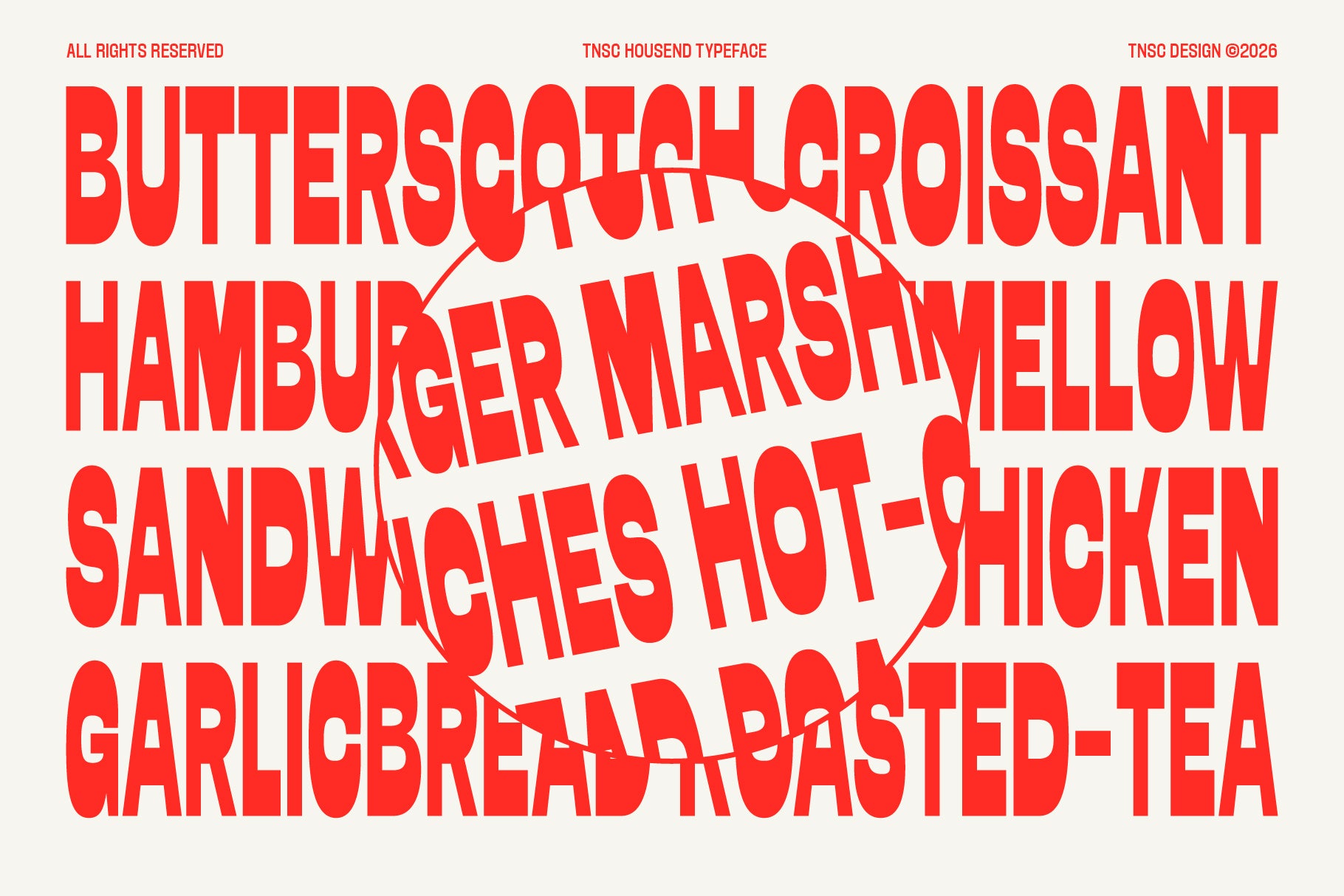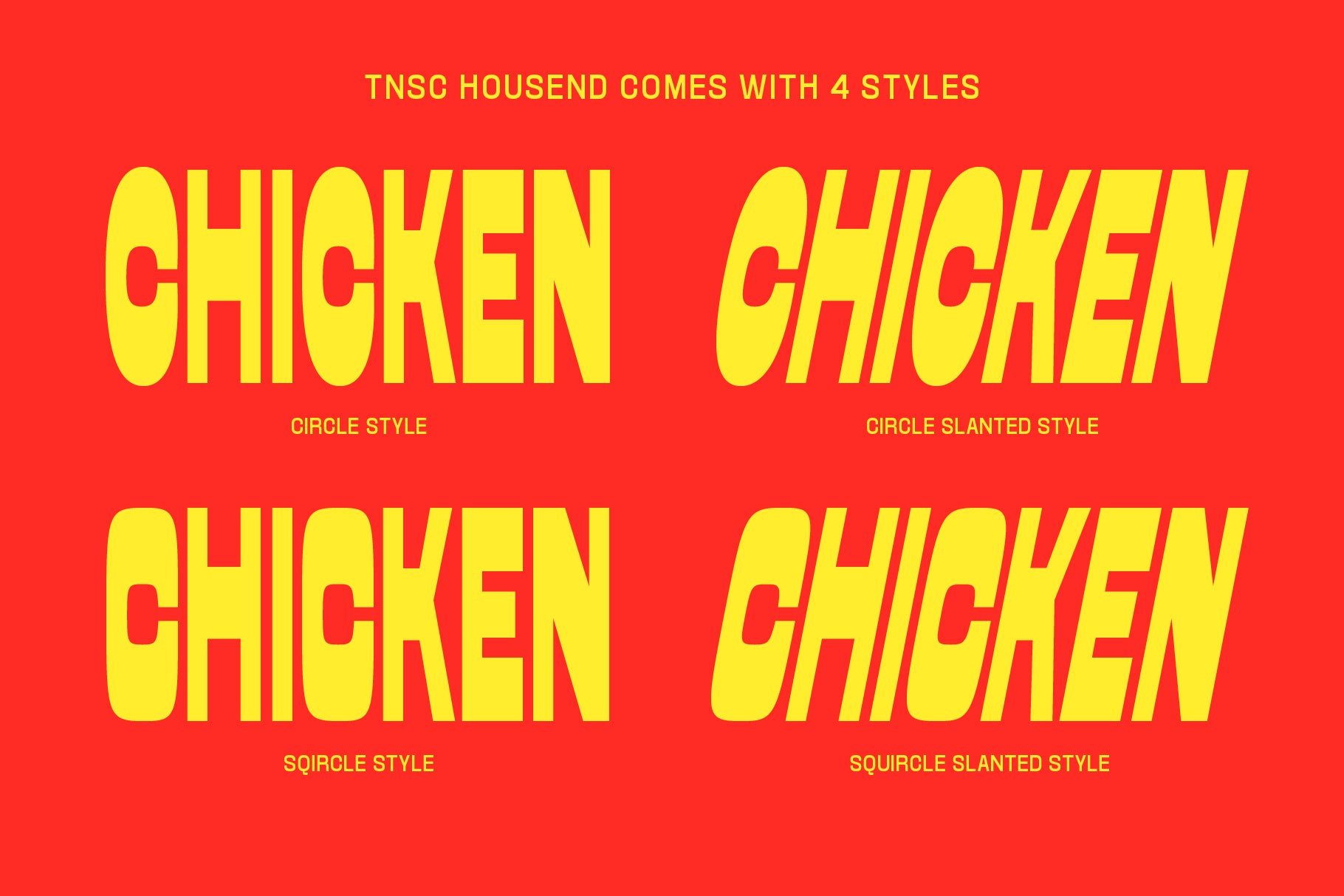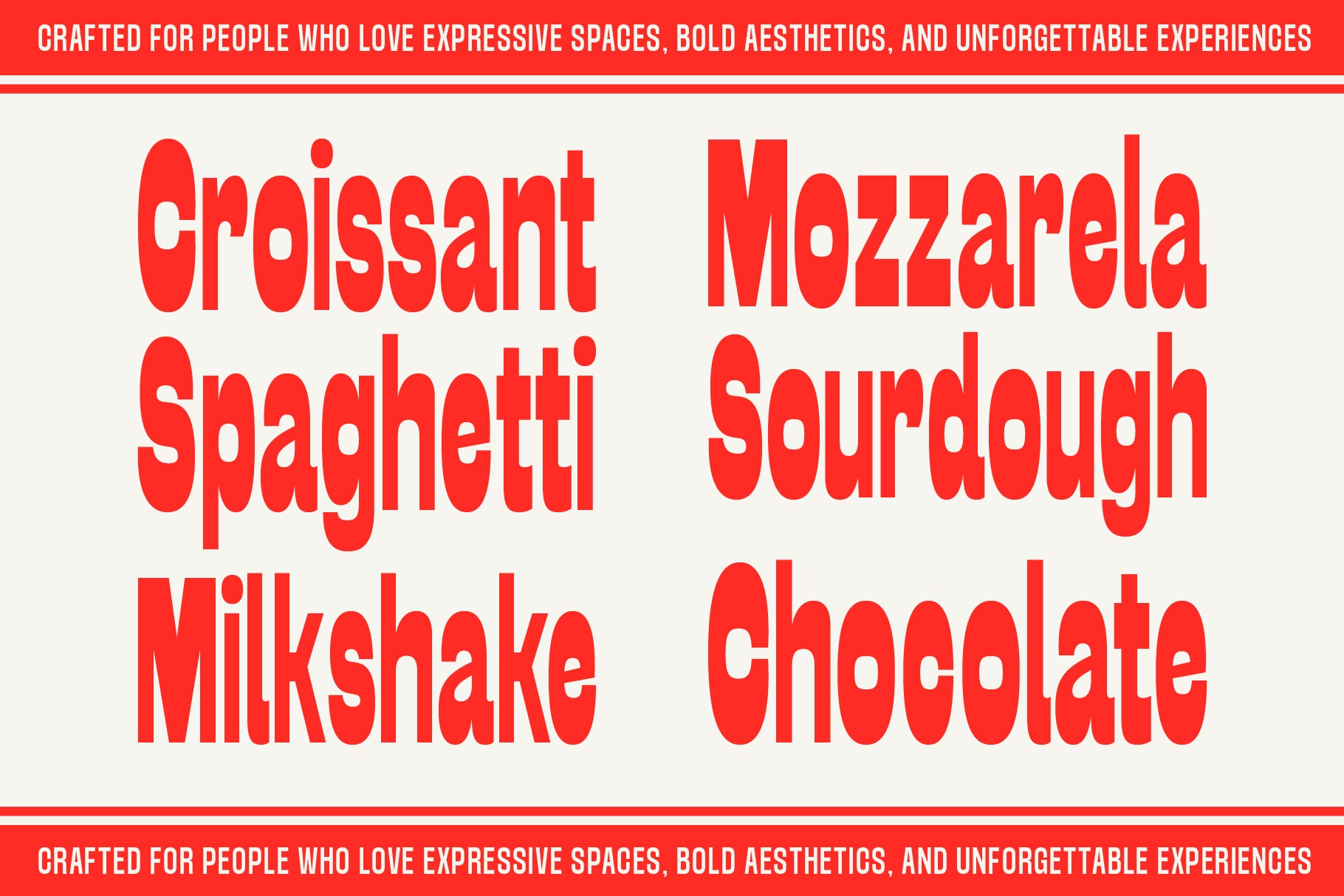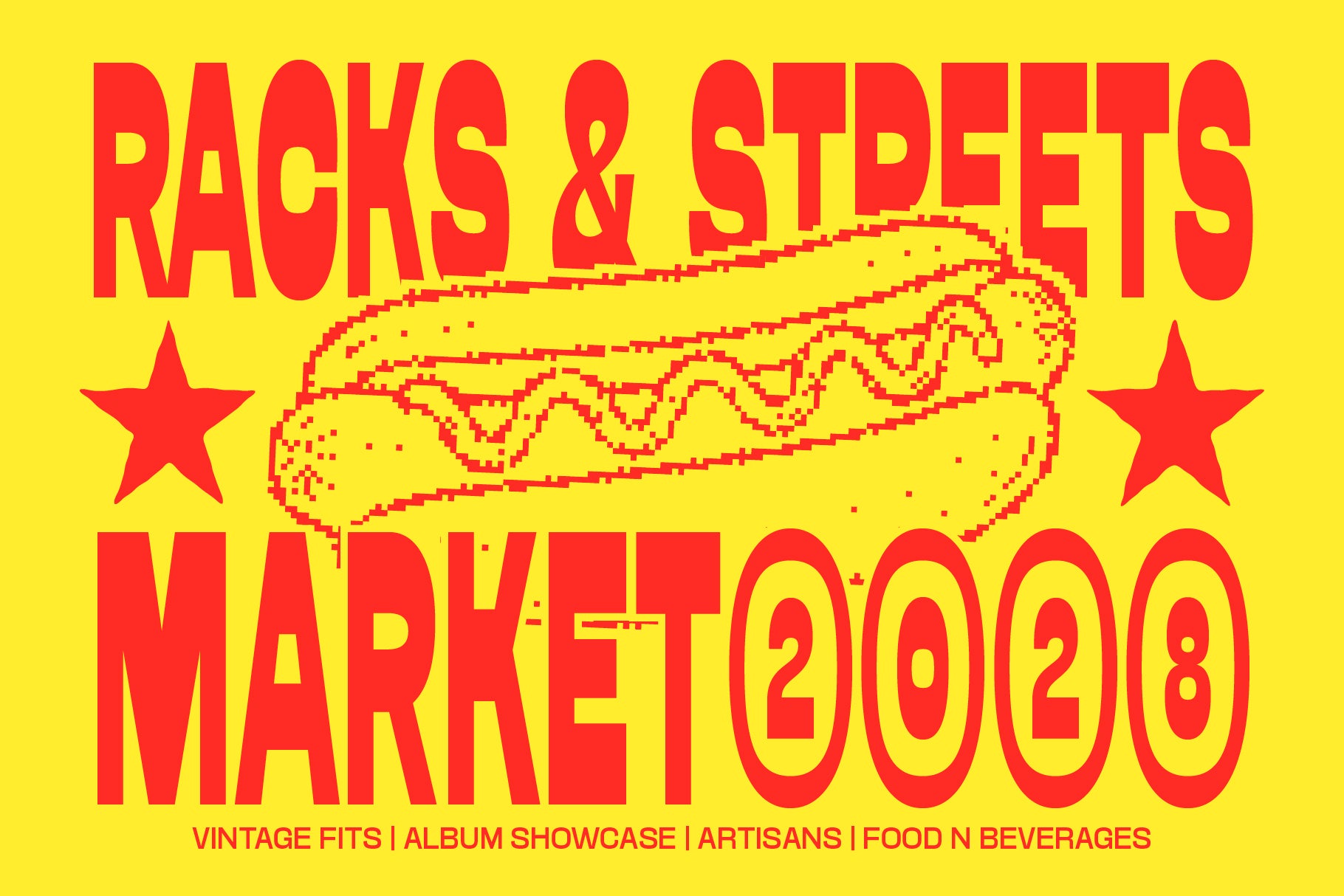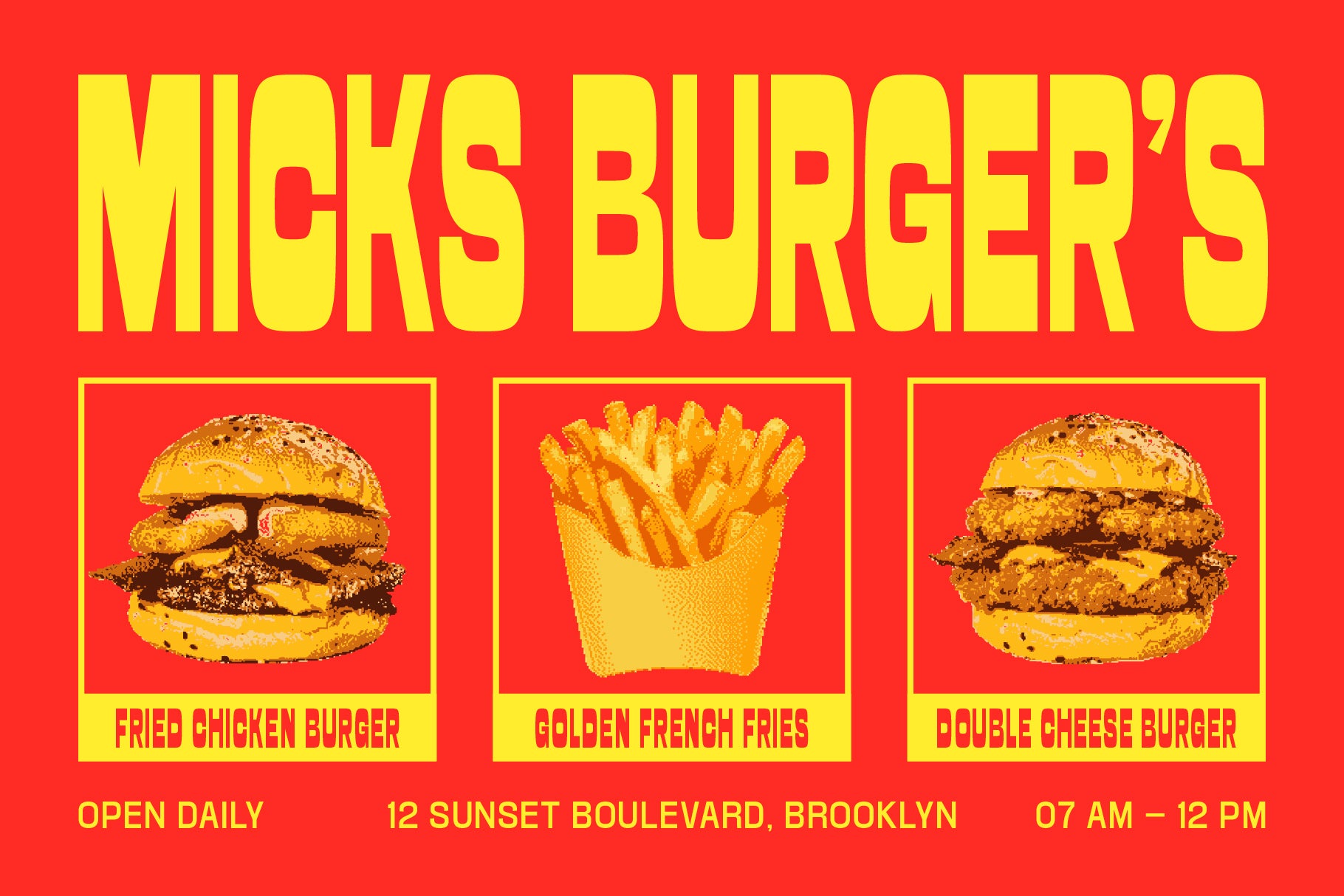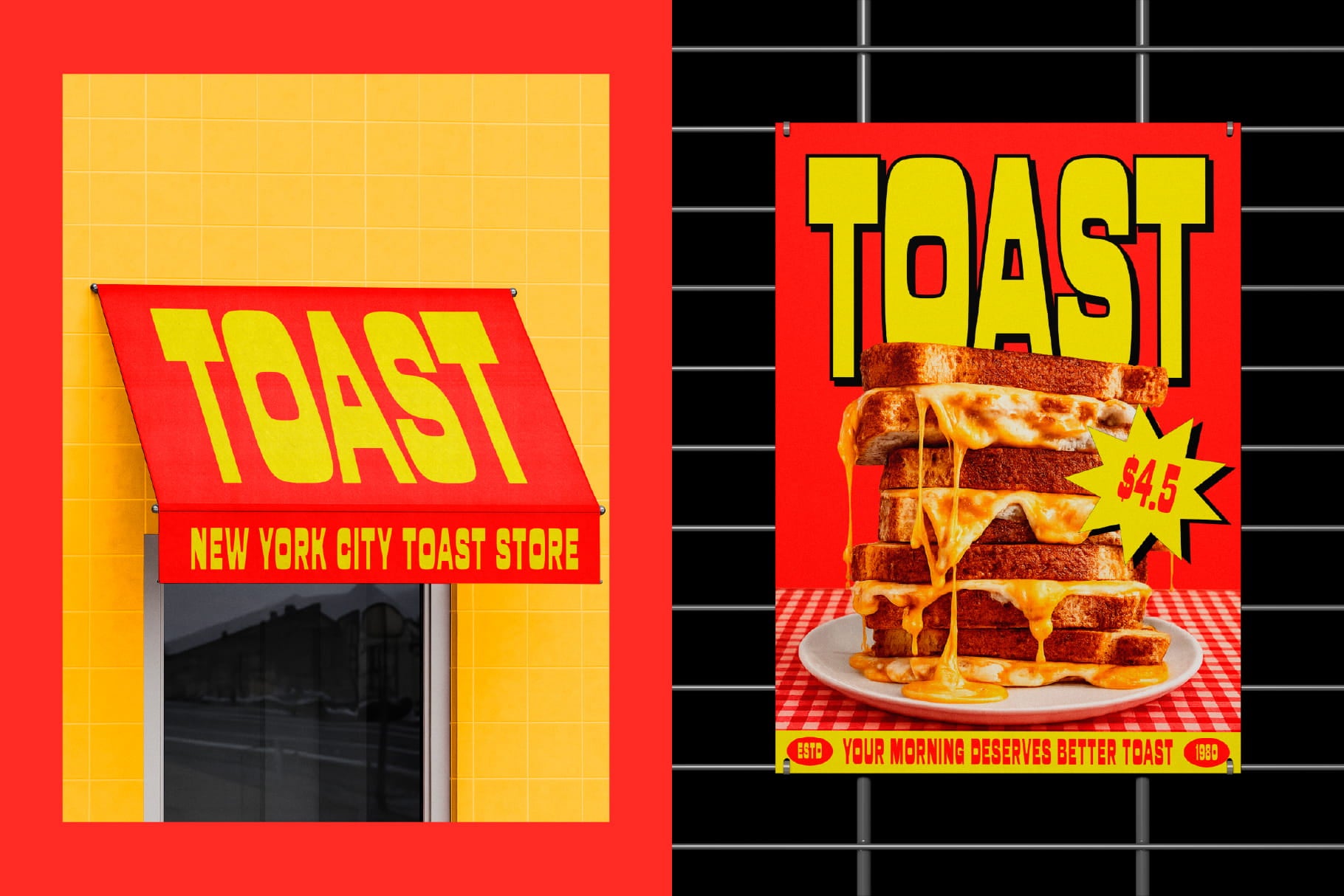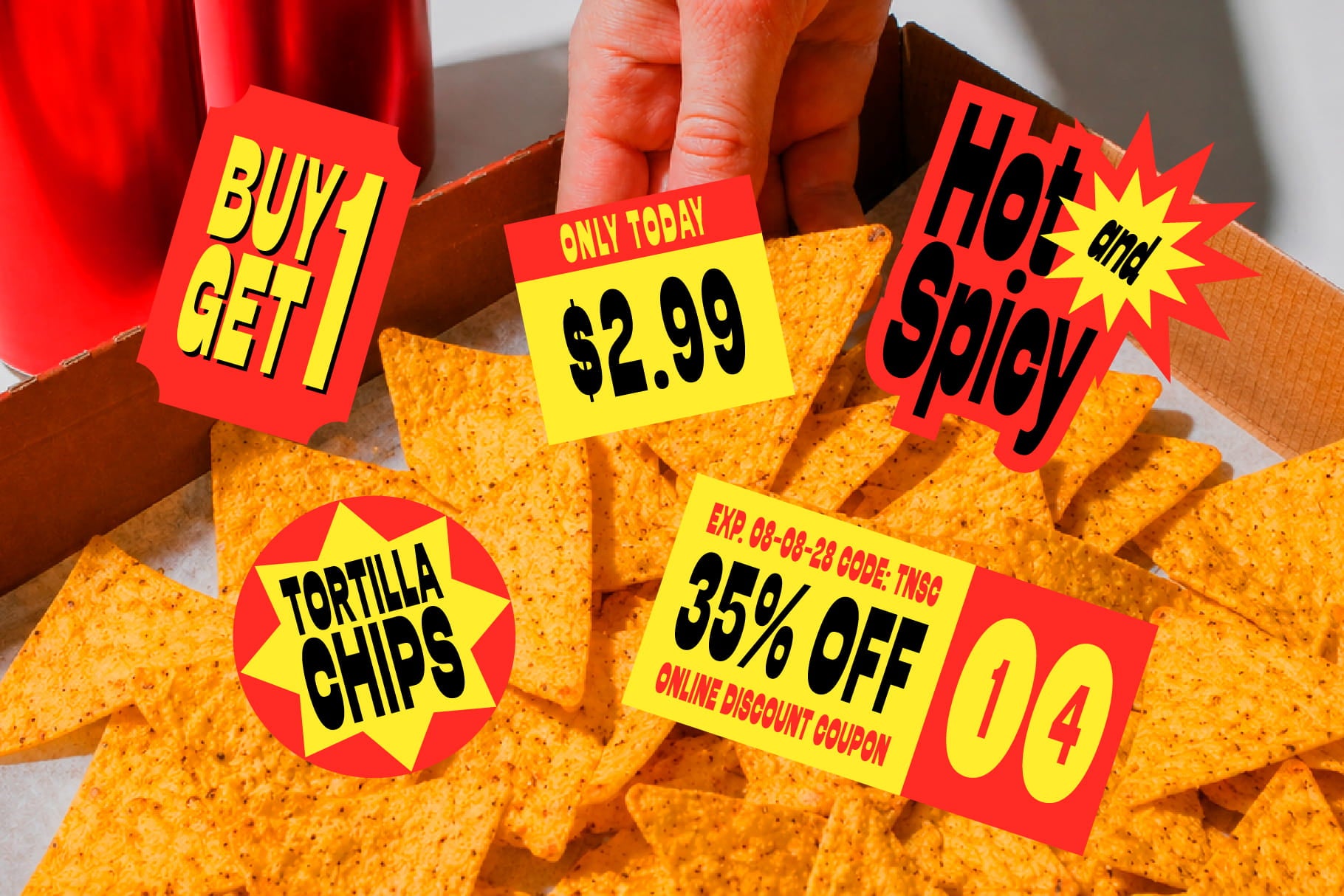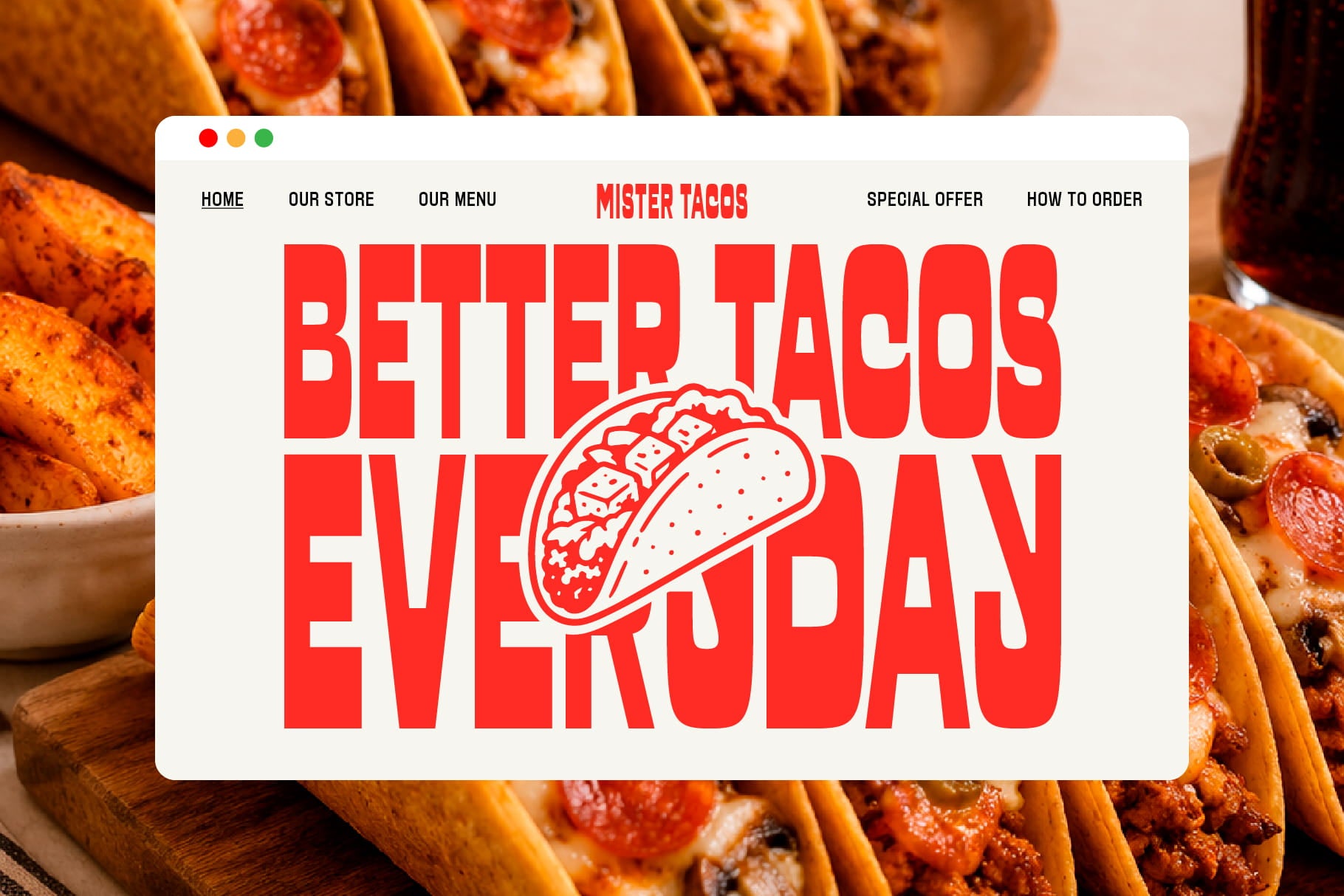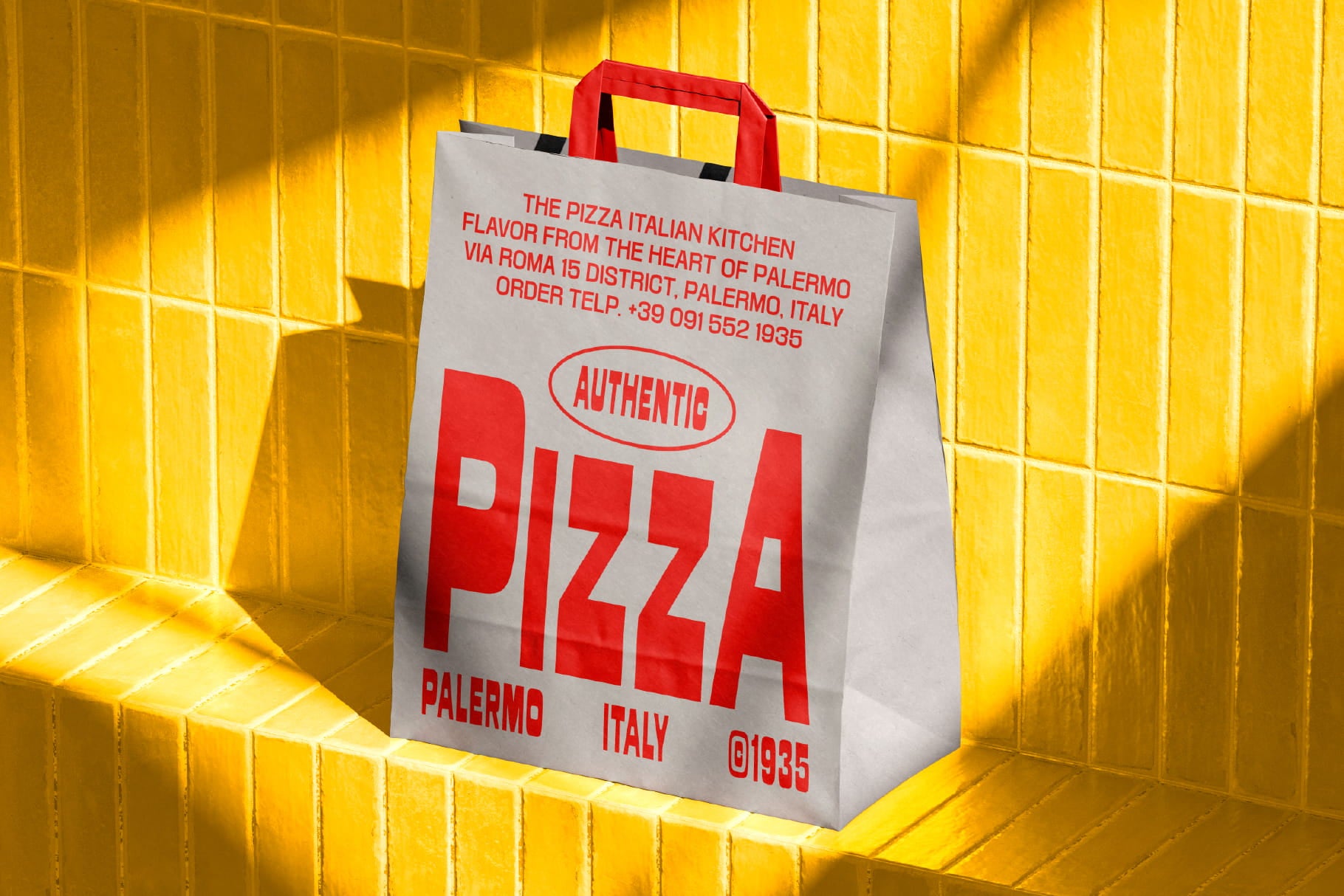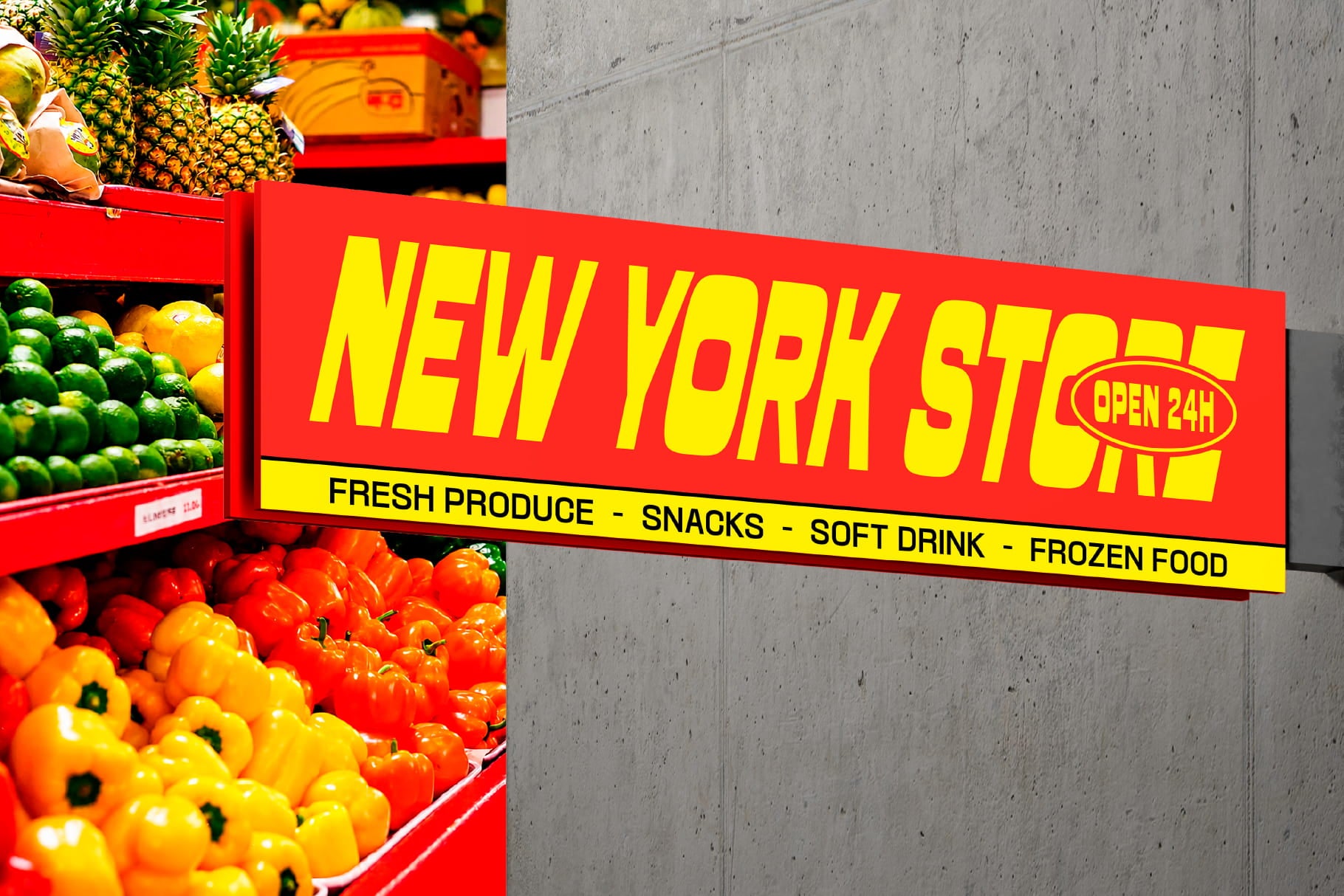
Fonte Housend TNSC
Housend é uma fonte condensada de contraste reverso, com uma personalidade ousada, excêntrica e divertida. Criada com formas altas e estreitas e proporções expressivas, essa fonte causa um forte impacto visual em qualquer design que precise transmitir ousadia, diversão e muita personalidade.
Inspirada em cartazes de comida, letreiros de feiras de rua, embalagens retrô, lanchonetes de hambúrguer, rótulos de salgadinhos e artes comerciais ousadas, Housend é perfeita para criar títulos chamativos e imagens de marca memoráveis. Seu contraste reverso único dá a cada palavra um visual saboroso, cheio de energia e um tanto inesperado.
A fonte vem em 4 estilos: Circle, Circle Slanted, Squircle e Squircle Slanted. Cada estilo oferece uma atmosfera diferente, mantendo o mesmo sistema divertido de fontes para títulos, o que facilita combiná-los em cartazes, cardápios, embalagens, letreiros, adesivos, roupas e artes para redes sociais.
• 509 glifos
• 4 estilos (Circle, Circle Slanted, Squircle, Squircle Slanted)
• Minúsculas
• Maiúsculas
• Diacríticos
• Alternativas
• Numerais (3 conjuntos)
• Pontuação
• Símbolos
• Moedas
• Matemática
• Setas